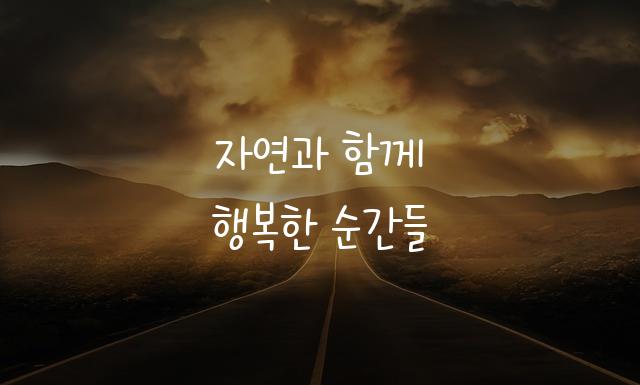
‘국립공원 반달이’는 국립공원공단에서 제작한 폰트로, 귀여움과 동글동글한 형태가 특징인 폰트입니다. 자연스러움을 기반으로 디자인되어 편안한 느낌을 줍니다.
국립공원 반달이은(는)
둥근 스타일, 귀여운 스타일, 감성적인, 자연감성, 부드러움, 복실복실 계열의 생김새를 가지고 있으며
어린이 책, 인사말 카드, 카페 메뉴 등에서 자주 활용되며, 효과적인 메시지 전달에 적합합니다.
이 폰트는 교육, 유아/가족, 환경/에너지 분야에 잘 어울리며,
귀여운, 편안한, 자연스러운 느낌을 담고 있는 것이 특징입니다.